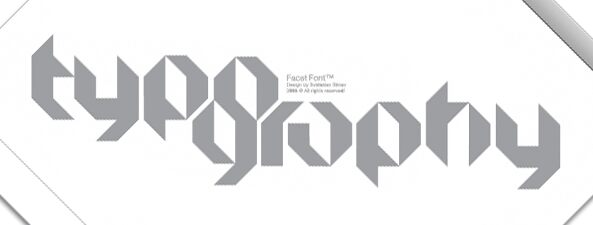
Facet Black, zaprojektowany przez Svetoslava Simova dla Fontfabric, to darmowy, futurystyczny font typu display, zbudowany z ostro zakończonych, fasetowych liter. Grube kreski, ostre cięcia ukośne i kanciaste prześwity nadają krojowi wygląd giętego metalu lub inżynieryjnego emblematu.
Świetnie pasuje do brandingu technologicznego, logotypów gier, plakatów eventowych, okładek płyt oraz kinowych napisów w klimacie sci-fi lub industrialnym. Jako darmowy font, Facet Black najlepiej sprawdza się w krótkich nagłówkach i zwartych znakach słownych, gdzie jego dramatyczne, wycinane formy mają wystarczająco dużo miejsca, by zdefiniować kompozycję.